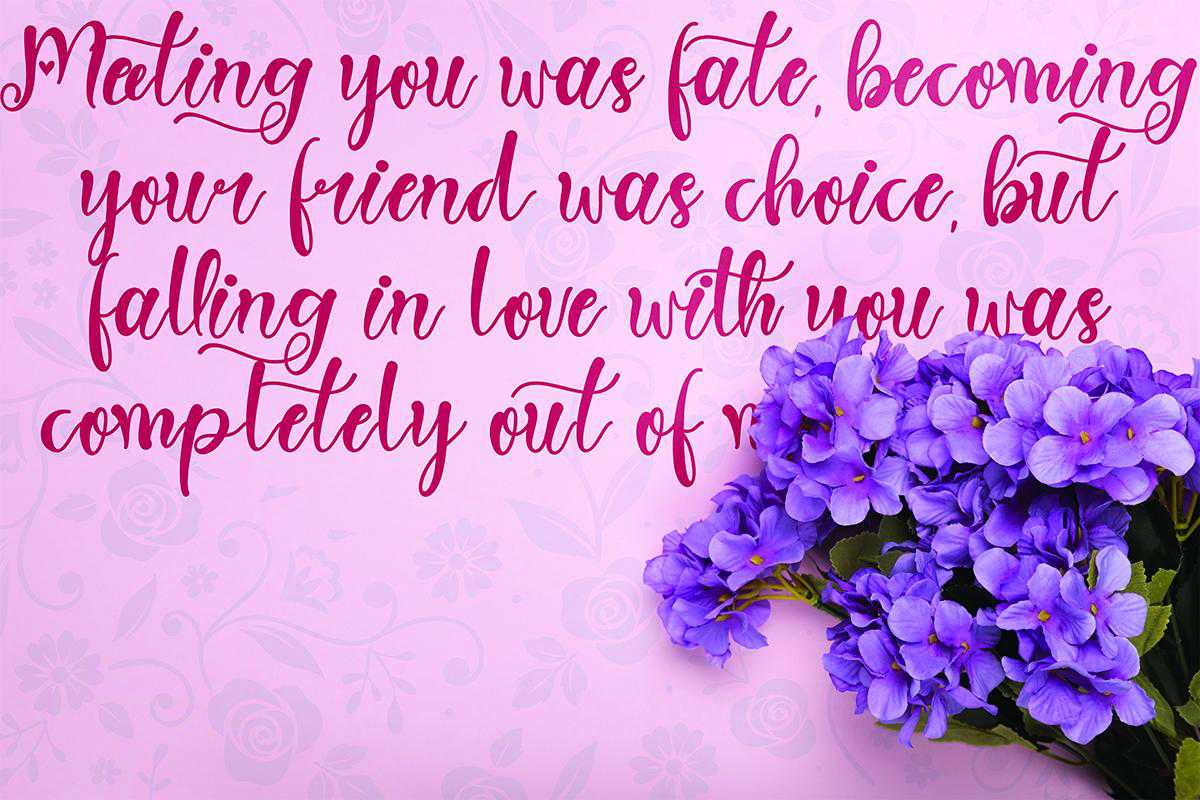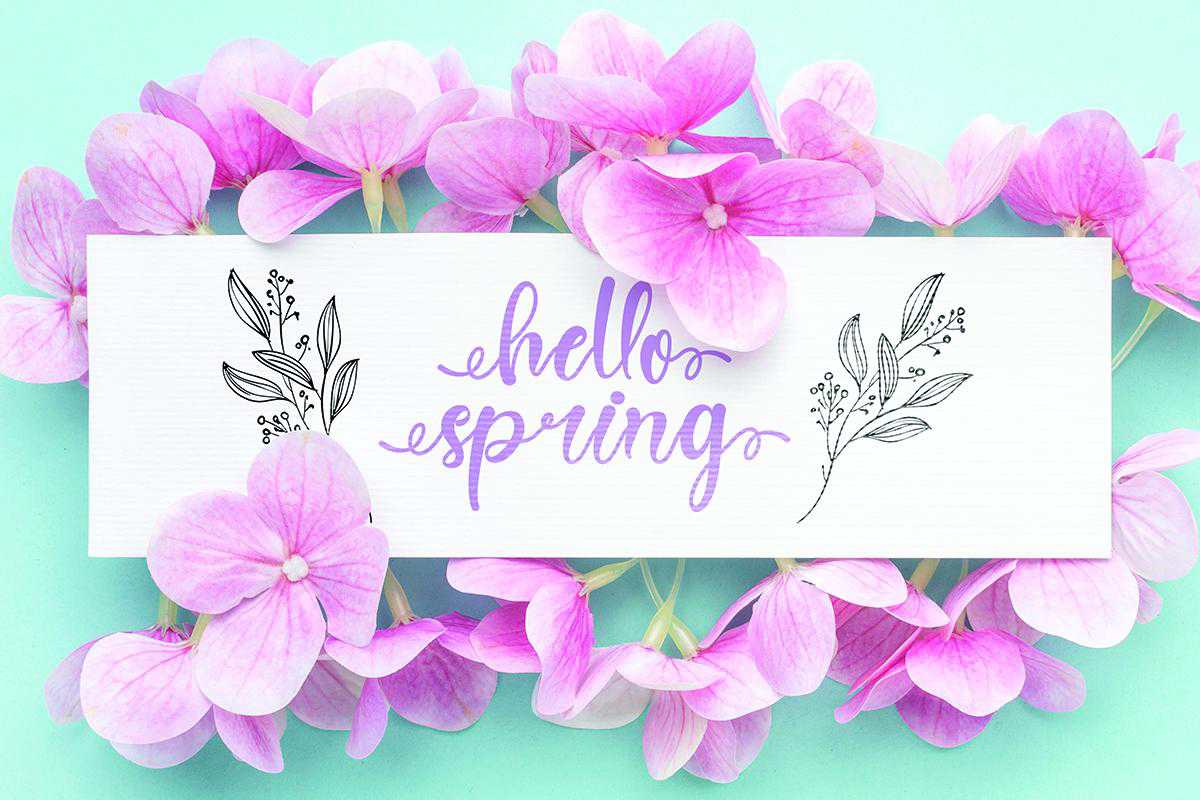
这种香型被称为“春心”,它结合了春心和春心。这种香型非常美丽、独特,而且是独一无二的。除此之外,月饼上的标签每年都很有用,并且有关于如何使用它们的说明。这种香型非常适合春天、婚礼、母亲节、父亲节、父亲节、复活节、地球日,和其他项目。这款香水被称为“春心”,它结合了春天和舒适的心。这款香水非常漂亮、独特,而且非常适合于各种各样的装饰。这款香水每年都会出现在手机上,而且还有关于如何使用手机的说明。这款香水适用于春天、婚礼、母亲节、父亲节、父亲节、复活节、地球日和其他项目。